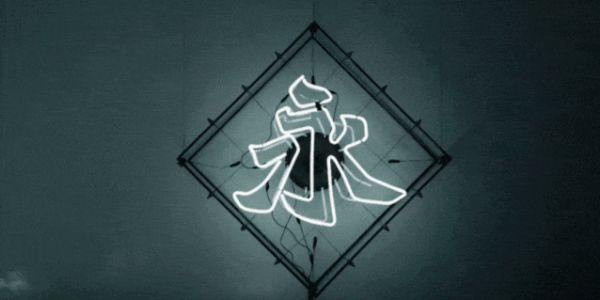
你还在用没个性的黑体字吗?
你还在使用没性格黑体字吗?点阵字、矢量字、衬线体、无衬线体...... 或许你还不了解这些关于字体的专业知识,但从街头巷尾,到直播弹幕,我们每天有着无数次与字体的相遇。本期字体特辑,为你带来7个设计事务所的字体设计实例,来看看这些设计师的“造字”故事吧。
01
“香港北魏真书”的历史根源可回溯自南北朝时期,后世清末赵之谦取法北朝碑刻,碑派技法体系得以进一步完善发展。作为藏在街道、商铺与日常中的“铁划银钩”,“魏碑字”是中国清末到民国时期一种流行的商业字体,🕰 而在1940至1980年代中国香港民间广泛流行的“香港北魏”,是当时民间流行魏碑字的一个缩影和地域性变体,亦是另一个时代里香港城市面貌的一幅招牌。2012年,由字体设计师、叁语设计合伙人/设计总监陈浚人发起的“香港北魏真书”字体项目,正是源自北魏书法的历史文化和创作精神,以及“北魏体”在香港民间的前世今生。
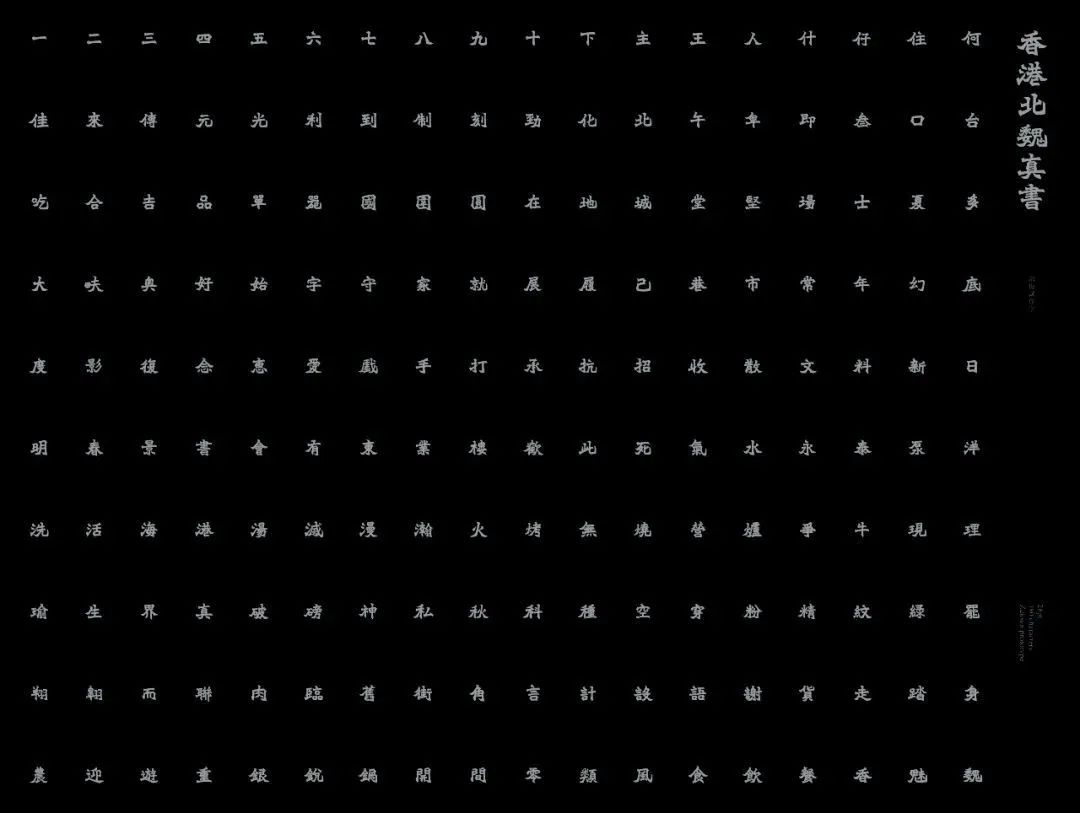
“香港北魏真书”字体设计细节。
卷宗 Wallpaper*对话
字体设计师、叁语事务所设计总监陈浚人 简称 A
W* "香港北魏真书"基于地道的中国香港本地商铺招牌,能否先介绍一下这背后的历史?
A:“香港北魏”是中国香港在上个世纪40至70、80年代广泛应用的字体,常见于招牌、广告、书籍封面题字、甚至墓碑等等,其普及程度有如欧美 Helvetica 字体。“香港北魏”字体风格源自魏晋南北朝时期的北朝碑刻字体,而经历清代书法家赵之谦的演绎,以及香港书法家区建公、苏世杰、卓少衡、黎一鸣、杨佳等的演绎及应用,“香港北魏”成为了香港独有的一种字体风格。我设计的“香港北魏真书”是以这种字体风格为蓝本,然后以现代的设计思维去重新绘画。
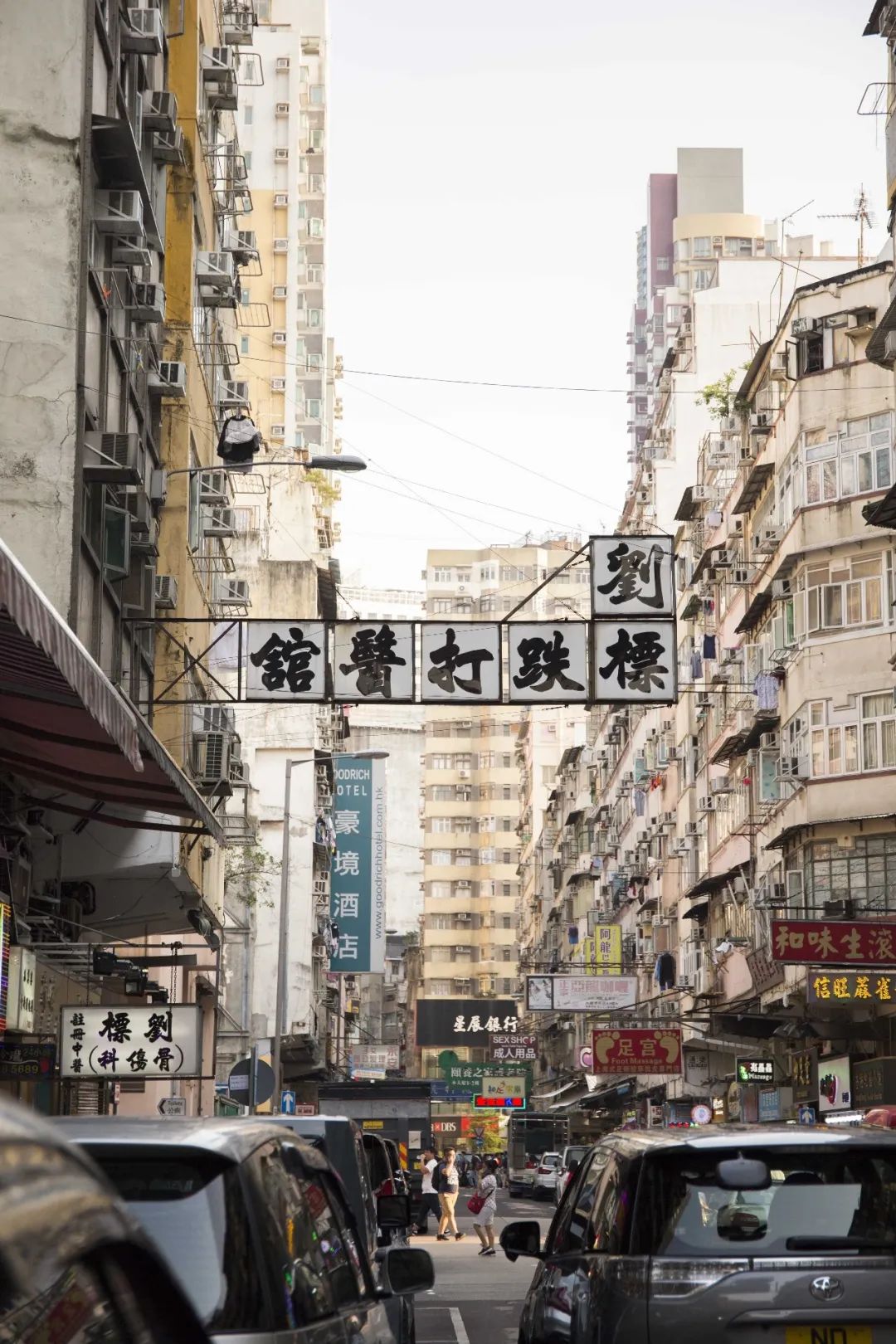
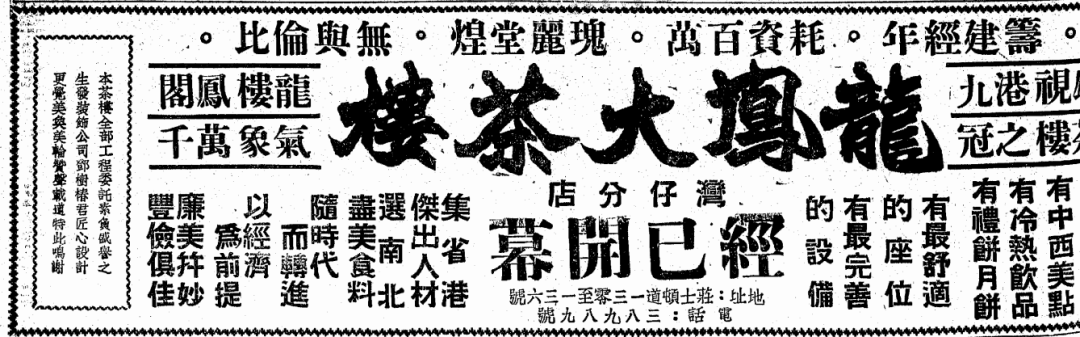
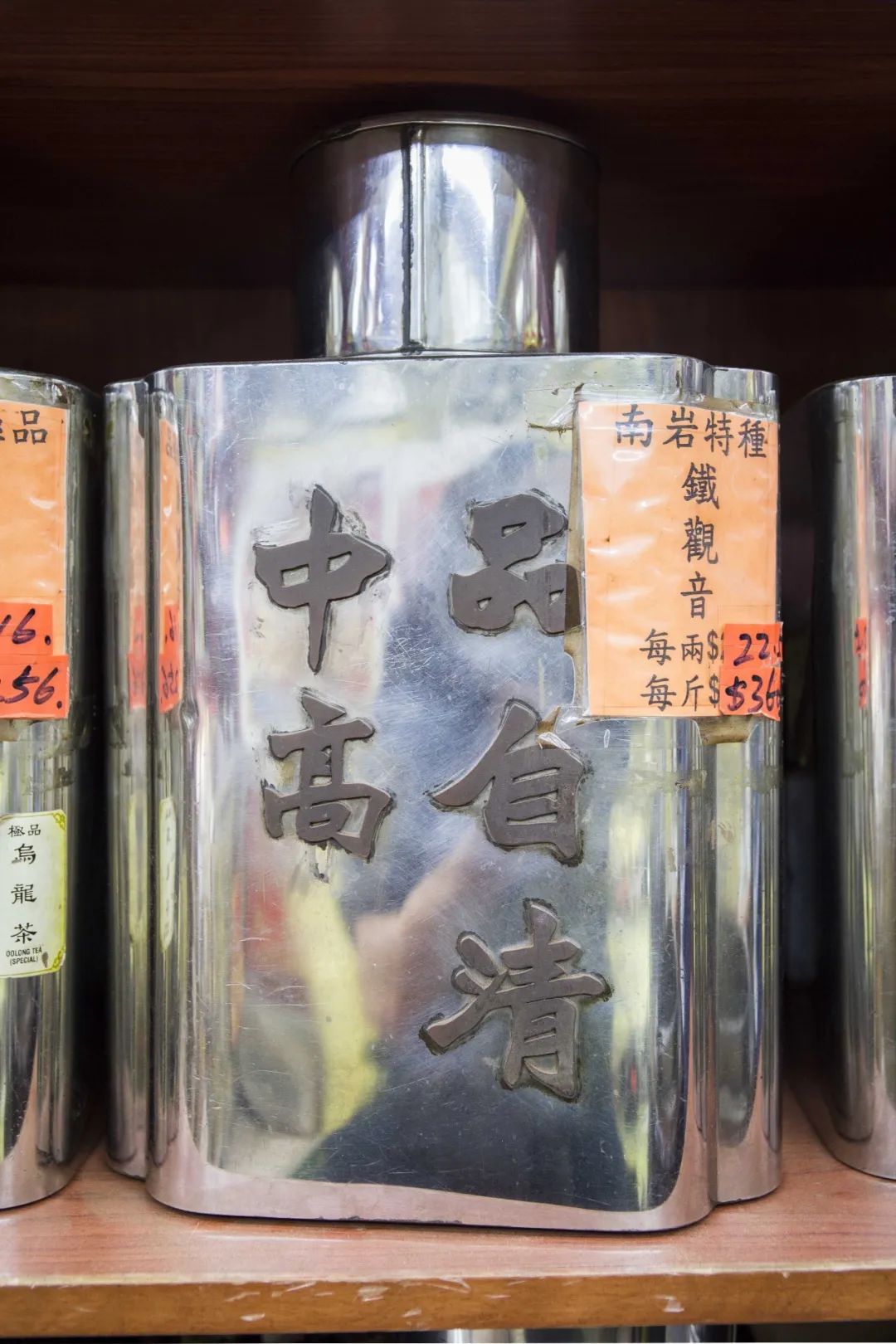
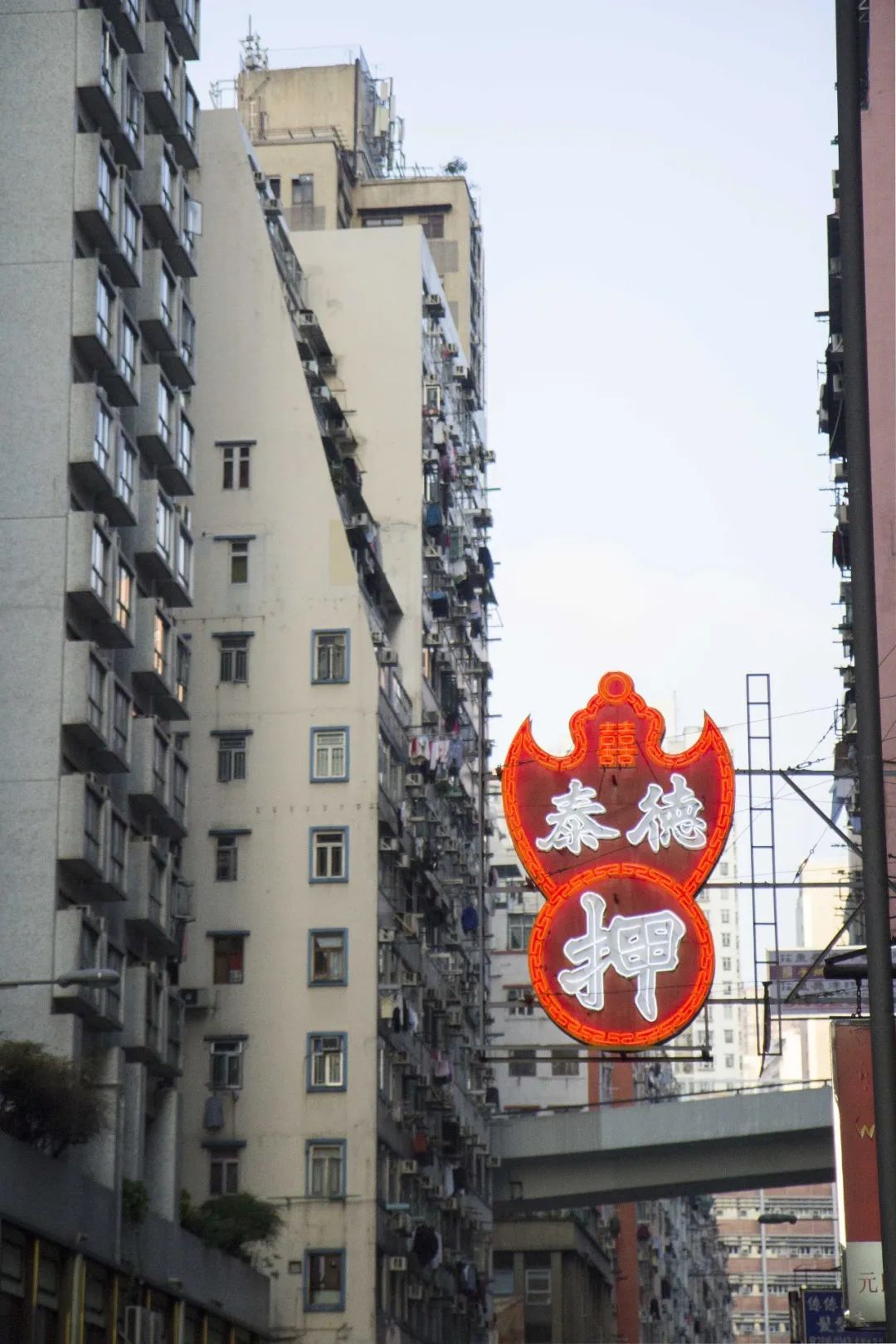
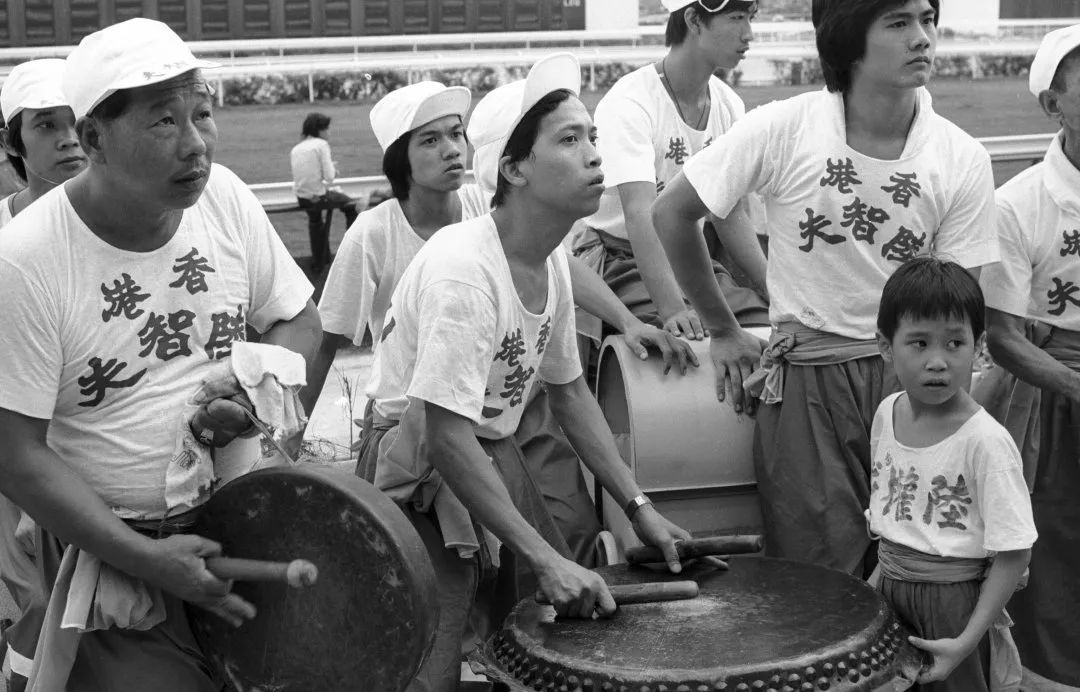
“香港北魏”是中国香港在上个世纪40至70、80年代广泛应用的字体,常见于招牌、广告、书籍封面题字等等,其普及程度有如欧美 Helvetica 字体。图片来源:陈浚人
W* 在设计上,怎样做到结合日常市井元素,并吸纳魏碑书法精妙之处?能结合比划、外形等细节讲一下吗?
A:我的字体设计着重实用性及文化延续,所以必须有严谨的统一性之余,又不失灵动。虽然源自书法,却不是书法字体,刻意删减书法纸笔墨的质感,只保精粹的线条及形态,强调当代的字体应用。设计思维类似楷书演变成明体字的过程,由书法漫漫统一成横平竖直的印刷字体。“香港北魏真书”比其他字体难处理,是因为结构变化多端,笔划收放幅度可以相当大,是产生强烈节奏感的元素,也同时是字体统一性的最大难题。
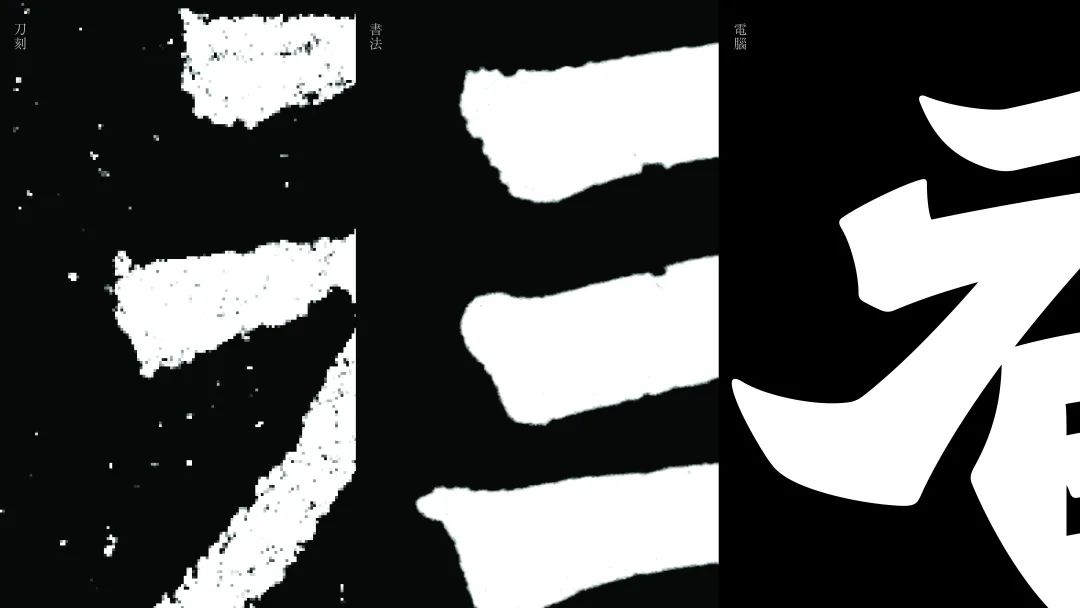
“香港北魏真书”字体设计细节。
W* 这是一种消逝中的字体,通过电脑再设计被存留,你们在做字体设计的同时也是在对城市视觉文化做一种梳理,谈一谈这其中的过程吧?
A:设计“香港北魏真书”的目的是透过有系统的研究,从历史、文化、美感及实用角度去审视这种字体的价值,从而由这些基础去思索设计的方向及目的。整个项目强调日常生活应用,“活”的文化,而非怀缅过去的情绪。亦希望做到一个示范,如何以设计思维审视香港的视觉文化遗产。研究过程尽量以第一手资讯为主,尽量探访与“香港北魏”有关的人物,也尽量搜集实体招牌、纸品等等。而近年香港的市区重建及高地价政策令大量老店结业,而珍贵的招牌也随之消失,所以是一项与时间竞赛的研究。虽然香港独特的城市风景面目全非,令人痛心,但我相信设计师如果能意识自己在文化建构的位置,这个城市的未来将会更精彩。
《香港北魏真书》内页及相关资料。
W* 你们也做了不少与字体相关的线下及衍生活动,能介绍一下吗?
A:我的设计公司“叁语”主要从事视觉传意设计,包括品牌设计、视觉识别、展览设计、书籍设计等等,而“香港北魏真书”是我们自发的文化研究及字体设计专案。“香港北魏真书”会应用在一些商业品牌设计专案例如“奥卑利”餐厅,也会应用在一些多媒体装置艺术品如“字无言”等等。“字无言”是一组八个霓虹灯字的互动装置,每个霓虹灯都配以一个电子吉他的收音器及扩音器,当观众将手放近霓虹灯字,预设的程式就会按照距离控制灯光闪动频率,吉他收音器就会放大霓虹灯的噪音,仿如一套噪音乐器。
《字无言》是一组八个霓虹灯字的互动装置,每个霓虹灯都配以一个电子吉他的收音器及扩音器,当观众将手放近霓虹灯字,预设的程式就会按照距离控制灯光闪动频率,吉他收音器就会放大霓虹灯的噪音,仿如一套噪音乐器。©️ Trilingua Design
03
“关于‘预测’,古人靠形象,现代人靠数据”。这份据说“预测了2020大事小情的新闻报纸日历” 🗓,听起来似乎很疯狂。非白设计工作室更是针对2020年每个月份的特点,对应了一款自己设计的 Transtype 字体。翻转日历,重启2020的平行宇宙!
非白设计工作室的字体设计及字体月历。 ©️ 非白工作室
设计师、非白设计工作室总监虞琼洁 简称 A
新闻报纸听起来很酷,这份据说是“预测了2020大事小情的新闻报纸日历”,最初的创意怎么来的?
A:工作室有一个内部规定,就是遇到双数年出日历。在2018年的时候,我们也用了工作室设计的字体出了一款日历。2020年,总觉得是一个比较特殊的有纪念意义的年份,貌似每个人都对2020有所期待。
有一段时间,工作室的各位沉迷于查询国内某玄学通胜的每日推送,凶日来临前会努力遵循推文中的宜办事项,如早晨先用右脚踏进公司大门;下午跟同事喝一杯加了八滴奶的热咖啡。大家也没有真的很信(毕竟信心才是运势之源)这不过一场忙碌生活里的自娱自乐。但后来想想,其实也挺有趣,原本未知的明天被人提前告知剧情,无论来日是凶是吉,心中早已服下一颗定心丸。
非白设计工作室的字体月历 ©️ 非白工作室
关于“预测”,古人靠形象,现代人靠数据。无论痴人说梦的妄想、言之凿凿的承诺有否实现,都是对未来日子的期盼与展望。非白的女子天团想效仿预言家,对接下来这一年可能会发生的大事小情进行大胆的预测。于是,我们设计了二〇二〇新闻预测报纸——一份融合了报纸新闻概念的叙事性日历。原本想说自娱自乐吧,后来觉得独乐乐不如众乐乐。一方面想让大家看看我们的预言是否在故弄玄虚,一方面也是想此物寄托我们对大家的祝福,希望大家能认真过好每一天,关注身边大小事。预言家也有失误的时候,谁料疫情的爆发,导致我们绝大部份的预言无法如期而至,但根据可靠消息,在隔壁X3X时空,我们的预言正在发生。那些吵着“重启2020”的小伙伴,可以来看看原本的2020应该是怎样的运行轨迹。
Transtype 字体项目。©️ 非白工作室
每个月份都设计了一种相关的字体吗?
A:这份报纸内所呈现的字体皆来自 Transtype 字体实验项目。我们从中选择了12款各具特点的字体,来作为报纸日历的文本字体。
一月:模块化字体ROCK去呼应报纸版面的模块化网格,新年的第一月开始,关心身边大小事;